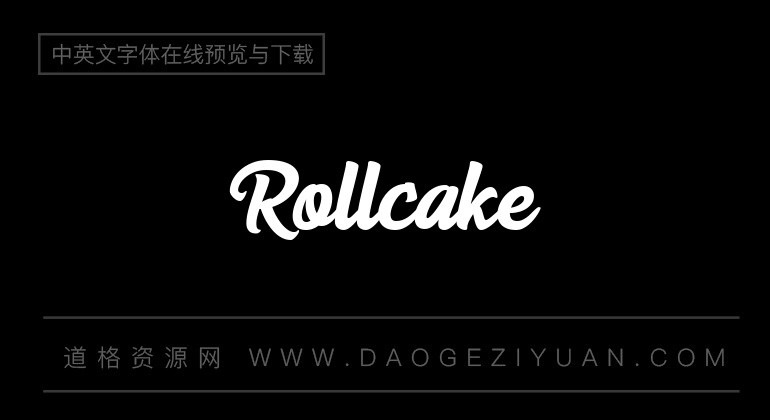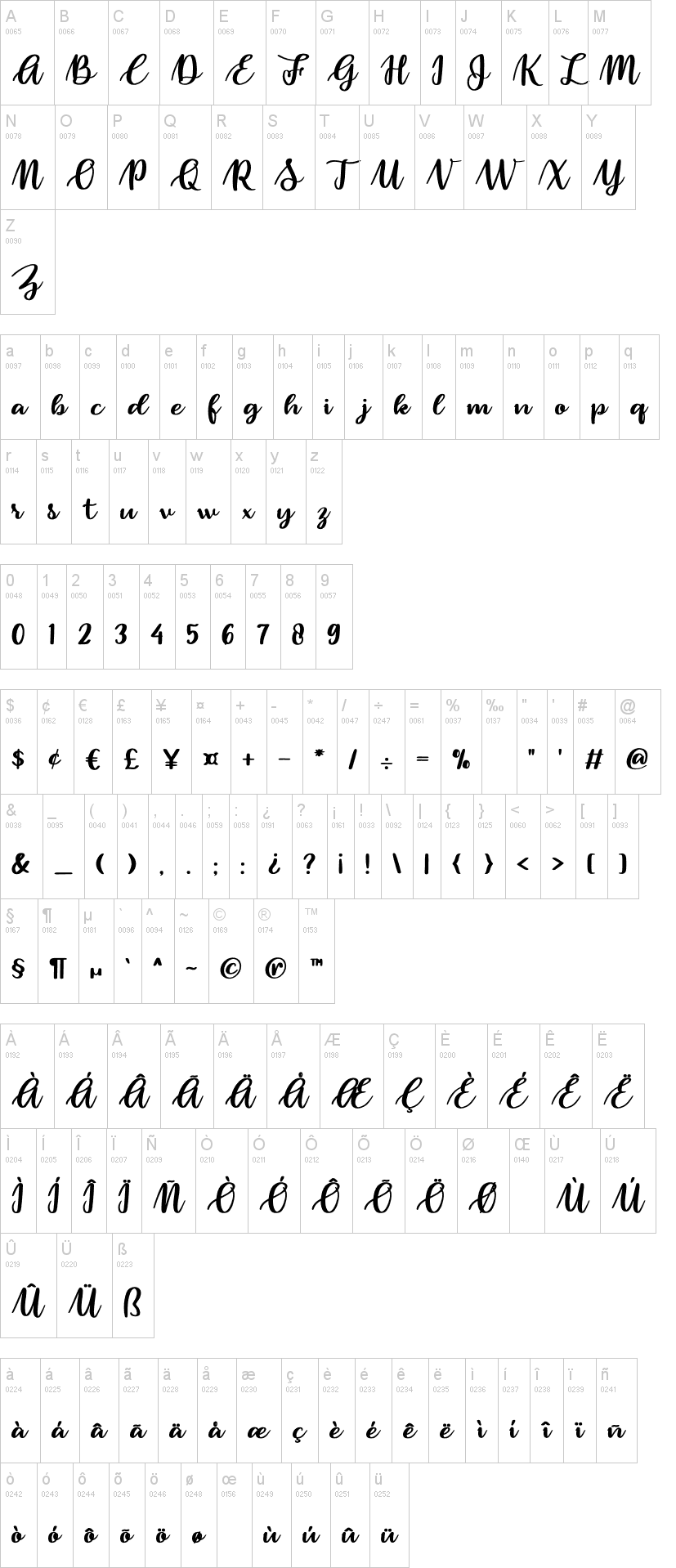
Rollcake
Rollcake 字体是一款由日本设计师Takashi Kawashima创作的英文字体。它是一种卡通式的字体,具有可爱的外观,曲线流畅,十分受欢迎。它的特点是其字母的外形精致,而且每个字母之间的连接线也比较精细,使得它更适合用于设计卡通形象。此外,它还具有良好的可读性,可以使文字更加清晰,更易于阅读。Rollcake 字体适用于各种印刷品,包括书籍、广告、海报等,也可以用于网页设计等应用。
Rollcake是一款非常不错的手写艺术字体,具有很好的视觉感,适合于文化类的宣传设计、商业类品牌的广告和产品包装设计以及个性化文字排版等较多场景。
Rollcake字符映射图